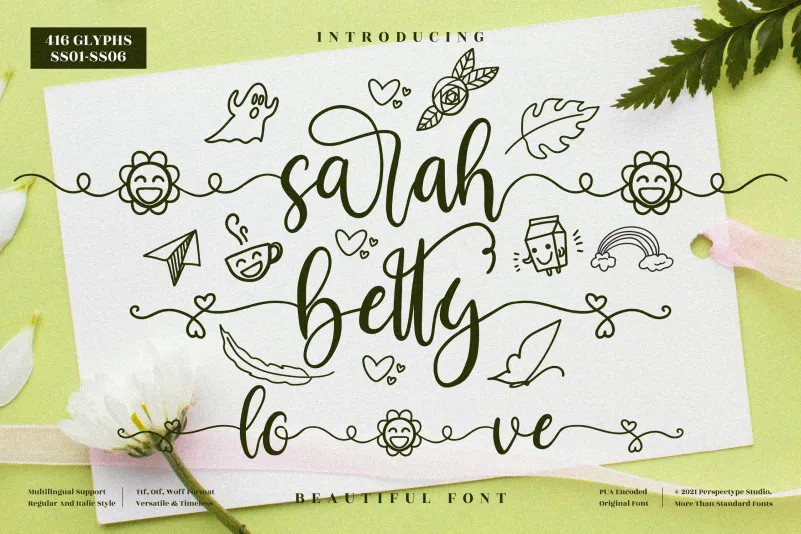
Sarah Betty Font – Download Grátis
A fonte Sarah Betty Font é uma elegante escrita à mão com um toque único e uma impressão impressionante. Perfeita para aqueles projetos que buscam dar um toque de luxo ao seu design, seja ele qualquer. Se você busca criar algo inovador e sofisticado, este é o remendo perfeito. Além disso, a fonte é PUA encodada, facilitando o acesso a todas as incríveis formas e ligaturas disponíveis. Esta característica de codificação oferece uma variedade rica de opções que podem ser usadas para criar textos únicos e interessantes em qualquer tipo de design. Seja você um designer gráfico ou uma pessoa amante da arte digitada, Sarah Betty Font é a escolha ideal para dar um toque sofisticado aos seus projetos. Tão versátil quanto única, esta fonte irá adicionar um toque diferenciador e profissional ao seu trabalho de design.